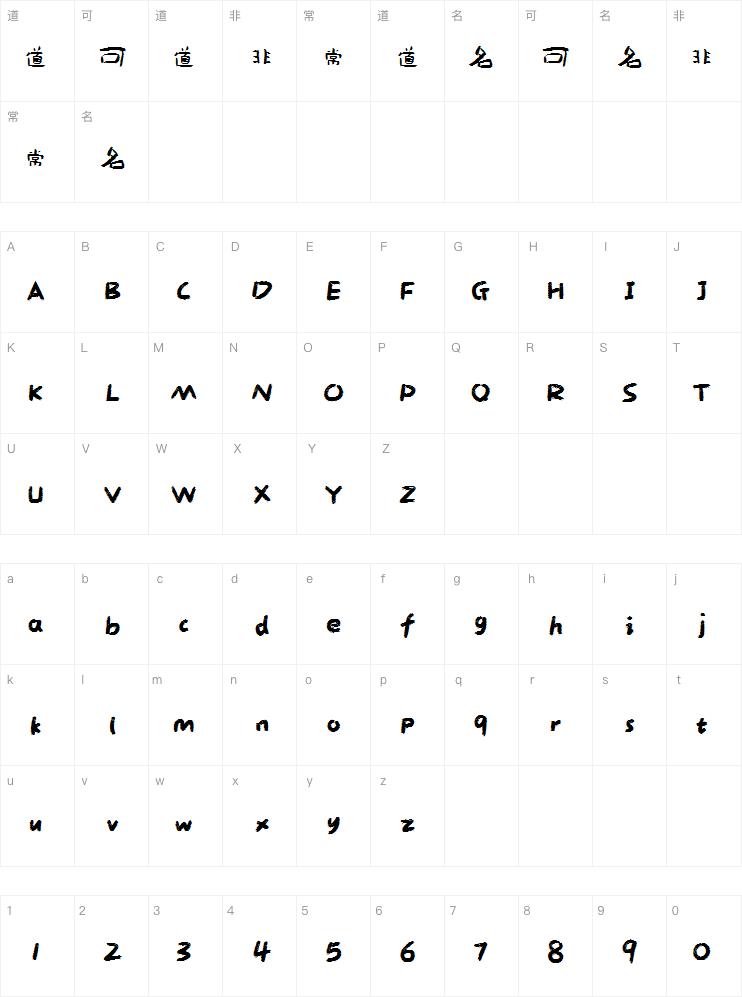
国风廉颇简体整体笔画简洁明快,结构较为规整,具有简体字的利落感。线条粗细相对均匀,笔画形态利落干脆,没有过多的装饰性笔画,体现出简约、清晰的特点,符合简体字便于识别和书写的需求,同时 “国风” 的命名可能让字体在简约基础上,带有一定的传统文化风格指向,整体风格偏向于实用且具一定设计感的简体字体,适合用于需要清晰、简洁视觉效果的文字呈现场景,如标题、宣传文案等。